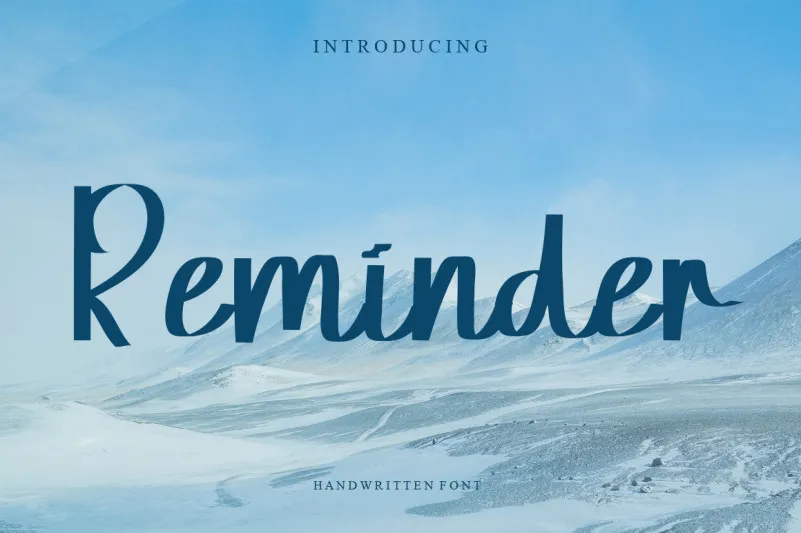
Reminder Font – Download Grátis
Esta fonte script é uma delicada, alegre e escrita cursiva. Ela se destaca com sua natureza suave e elegante que não só tornará seus projetos únicos, mas também adicionará um toque agradavelmente romântico e encantador a cada projeto. Seja em cartões de aniversário, calendários pessoais ou até mesmo em designs digitais, ela está pronta para transformá-los em algo especial e único. A fonte Script ‘Reminder Font’, criada por levincreative, é perfeita para aqueles que buscam uma mãozinha amável e encantadora para dar um toque final a seus trabalhos de design. Não hesite em explorar as possibilidades criativas desta fonte suave e delicada; certamente irá brilhar como o sol na sua próxima criação visual.